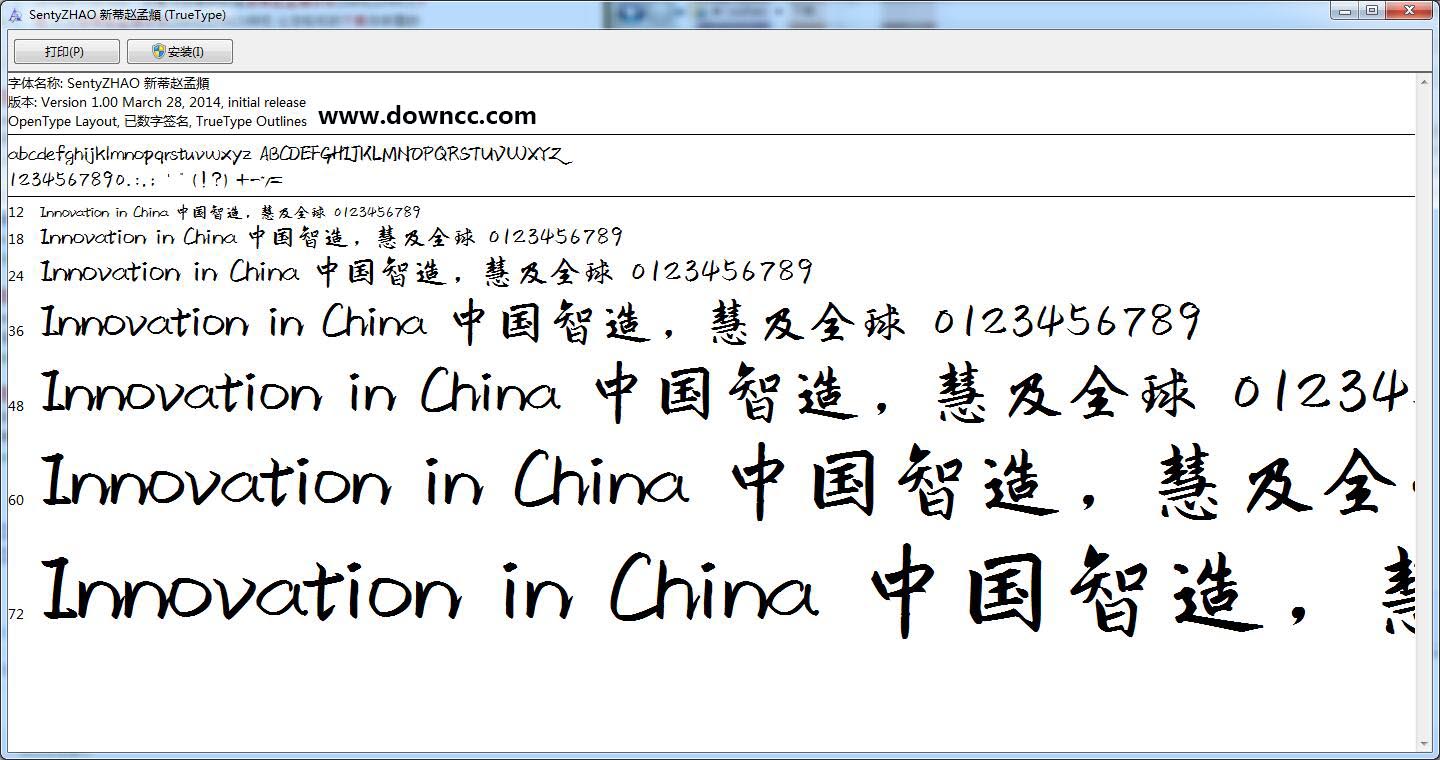
新蒂趙孟頫字體是根據(jù)書法家趙孟頫字體推出的字體應(yīng)用。這款字體同時(shí)支持中文、英語、法語等西方語言輸出,可以將文字變得有力度!喜歡這款字體的用戶可以來綠色資源網(wǎng)下載使用!
新蒂趙孟頫字體是一款比較霸氣的字體應(yīng)用,使用這款字體輸出的文字非常美觀大氣,可以用來編排文字,使用于廣告設(shè)計(jì)等行業(yè)!在新蒂趙孟頫體中以相同的書法風(fēng)格,加入了日文漢字、假名和日文符號(hào)。拉丁字母也擴(kuò)展了標(biāo)音符號(hào)(Diacritical),使得例如法語、德語、西班牙語、捷克語等語言都可以完整顯示。為多語言使用者和學(xué)習(xí)者提供了很大便利。以后還會(huì)不斷在字體更新中加入更多語言,特別是中國少數(shù)民族語言。